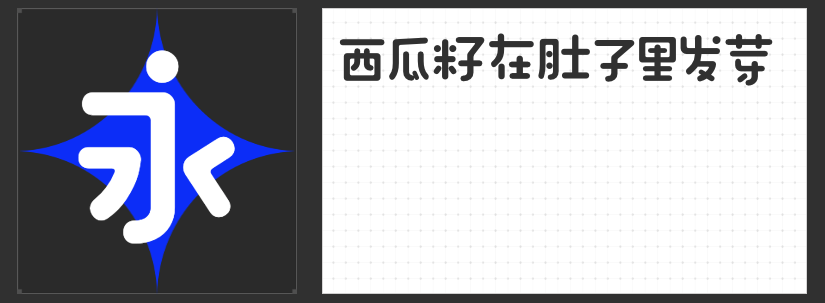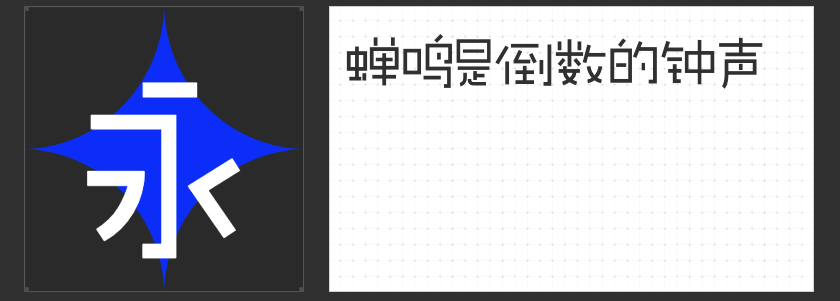
四款萌系字体推荐:用可爱笔触唤醒设计生命力
在追求个性化与情感共鸣的设计浪潮中,可爱风格字体凭借其独特的亲和力与治愈力,成为品牌年轻化、IP形象塑造及创意内容传播的“秘密武器”。以下四款风格迥异的萌系字体,以手写温度、几何趣味与潮酷态度,为设计注入鲜活生命力。
一、字恋狂澄空 拂风
这款字体以“上松下紧”的动态结构打破常规,重心微低的设计让每个字仿佛自带轻盈步伐。流畅的弧线与利落的直线交织,搭配平直切角的折笔处理,既保留手写温度,又消解了锐利感。笔画间的“留白呼吸”与灵活多变的偏旁占比,让文字组合如音符般跳跃,尤其适合儿童绘本、社交媒体表情包等场景。
二、励字造桃气圆 准粗
以“圆”为设计基因的桃气圆,用饱满的笔画包裹每个字符,内外圆角兼备的折笔设计,让文字如同吹泡泡般轻盈可爱。圆形元素替代部分笔画的巧思,搭配松弛有度的结构,营造出棉花糖般的柔软质感。笔画间的“断点处理”赋予字体呼吸感,无论是甜品包装、母婴品牌还是节日海报,都能瞬间传递温暖治愈的视觉信号。
三、字恋狂嗨玩简
粗壮的笔画与方块字形碰撞出奇妙反差,重心下压的设计让文字仿佛踮脚站立,自带笨拙的童趣感。这款字体如同用积木拼搭出的文字乐园,适合用于儿童玩具、潮玩IP或需要强化“萌系力量感”的创意海报,简单直接的视觉语言能快速拉近与受众的距离。
四、字恋狂拙黑简
以直线切割与横细竖粗的对比,构建出充满叛逆感的几何骨架,中宫舒展的设计却让这份锐利多了几分慵懒。连笔与手写化细节的点缀,如同在工业风中融入涂鸦笔触,让字体在潮酷基调中暗藏可爱基因。音乐节海报、街头品牌或Z世代社交内容,都能借其表达“不羁的温柔”。
这四款字体通过几何趣味与潮酷态度的创意融合,为可爱风格设计提供了多元表达路径。无论是追求治愈感、童趣感还是叛逆萌力,总有一款能成为你的“设计萌友”。